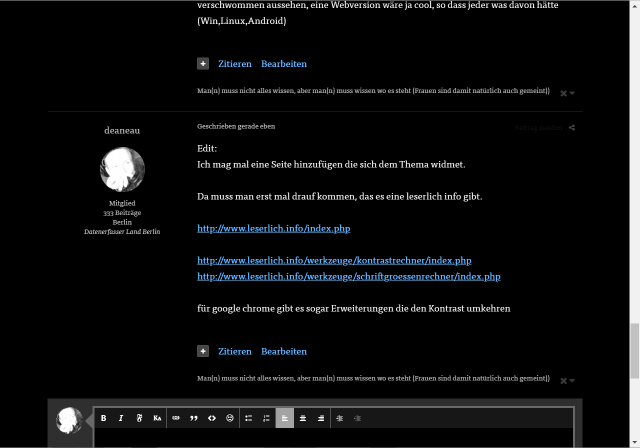
Beste Schrift für kleingedrucktes?
sagt mal welche Schrift ist für Euch für klein gedrucketes am besten geeignet, die auch noch für Brillenträger mit geringer Sehschärfe lesbar ist.
Hier ist ein normaler Leseabstand von Interesse. Soweit ich weiß, ist  Weiß auf Schwarz mit hohem Kontrast am besten geeignet.
Bei Drucksachen ist das auf der Rückseite einer   A4 bis A8 Seite sicher nicht wirklich praktikabel, da man ja soviel Schwarz druckt dass es unökonomisch wäre.  50% Schwarz oder weniger wäre sicher auch nicht gerade geeignet.
Gibt es denn Faustformeln die in Abhängigkeit der Schriftgroße zum Papier und der Schriftfarbe?
Es gibt ja die Norm DIN1450, aber ein Verein wird sich sicher nicht die die Kosten schmecken lassen.
Klar ist, je kleiner die Schrift je höher  muß der Kontrast sein.
gibt es denn Normen wie lang  AGBs etc. sein müssen / dürfen?
an diesem Beispiel hier AGB für Fotografen würde ich   jedenfalls die Seitenzahl reduzieren wollen.
Ich erinnere mich, dass es für gewisse Branchen gesetzliche/amtliche Mindestlesbarkeitsansprüche gibt. Das Weiß auf Schwarz am besten lesbar sei, müsste erst einmal bewiesen werden.
Beipackzettel sind gewöhnlich in einer Sans und wegen der Länge auf Dünndruckpapier gedruckt. Generell muss eine Lesbarkeit vorhanden sein, vielleicht muss auch schon Barrierefreiheit berücksichtig werden? Da es ein Vertragsgegenstand beinhaltet, würde ich die AGB immer in gewöhnlicher Korrespondenzgrößen (ist das Anschreiben in Sans 12p, sollte der Vertragstext das auch sein) halten. Platzsparen und dafür Lesbarkeit opfern, geht nicht, dazu gab es auch schon Urteile (die ominösen weiße Sans auf Hellblau in 4p).
Für den Text würde ich eine dem Medium angemessene Schrift wählen, vielleicht mich vom Zeitungsdruck inspirieren lassen, denn die haben auch das Platzproblem.
Die mit Windows ausgelieferte Schrift  »Sitka« hat einen  »Small« bezeichneten Schnitt. Damit lässt es sich auch in sehr kleinen Größen gut lesbar setzen. Allerdings spielt auch die Zeilenlänge eine Rolle.
Keine – ich bin der Meinung, dass sich beides ausschließt. Entweder ich will das berühmte "Kleingedruckte" setzen, dann gehe ich davon aus, dass das eh keiner lesen will oder soll, und halte mich an die gesetzlichen Mindestgrößen, sofern vorgeschrieben. Oder ich will, dass das von Menschen mit Augenproblemen ohne Hilfsmittel gelesen werden kann, dann ist es kein Kleingedrucktes mehr, sondern muss anders aufbereitet werden.
Aus konzeptioneller Sicht der Schriftgestalter gibt es da viele Möglichkeiten – oft verbunden mit optischen Größen, welche in ihrer Ausformung eben genau diese unterschiedlichen Größenanforderungen berücksichtigen. Für kleine Schriftgrade optimierte Schriftschnitte werden dann oft mit dem Begriffen »micro« oder »caption« bezeichnet, zum Beispiel hier:
But Zeitung has more to offer. Its optical sizes offer the best style for each size of your text. Zeitung fonts are devided to two optical families: Zeitung Standard and Zeitung Micro. Zeitung Standard works great in most sizes, while Zeitung Micro fonts are specially made for very small sizes in print and web. Zeitung Micro fonts are perfectly legible in web, where the same technical font styles have to survive in many environments, from older browsers to most up to date mobile screens.
PT Sans Pro is a comprehensive type family intended for a wide range of applications. It consists of 32 styles: 6 weights (from light to black) with corresponding italics of normal proportions; 6 narrow styles; 6 condensed styles; 6 extra condensed styles and 2 caption styles (regular and bold). The design combines traditional conservative appearance with modern trends of humanistic sans serif and possess enhanced
legibility especially in caption styles.
These features, besides conventional use in business applications and printed materials, make the fonts usable for direction and guide signs, schemes, screens of information kiosks, and other objects of urban visual communications.
Weitere Beispiele von Schriftfamilien mit optischen Größen für Kleingedrucktes:
Insbesondere für Kleingedrucktes optimierte Schriftfamilien:
Das Weiß auf Schwarz am besten lesbar sei, müsste erst einmal bewiesen werden.
Ich gehe mal von deinem Avatar aus das du auch Brillenträger bist. Ich habe das mal im Selbstversuch gemacht. hier könnte man es selbst schnell test ohne ein smartphone zu benutzen, einfach Maus über den Text und STRG-Taste +Mausrad soweit rauszoomen wie nötig.